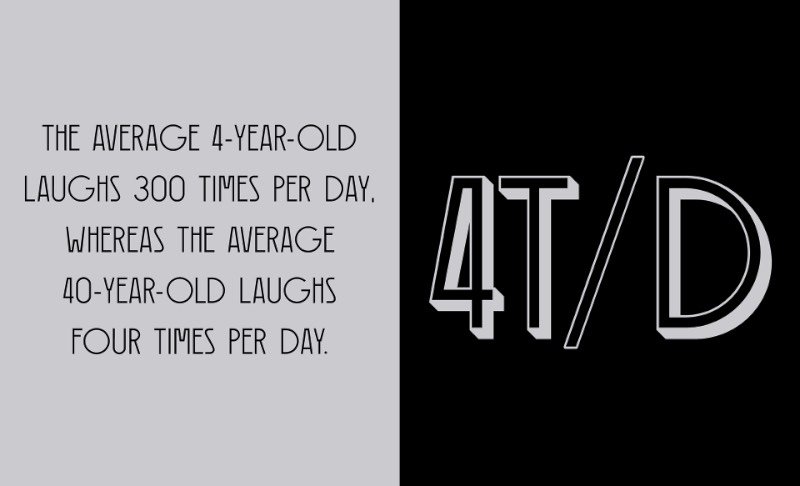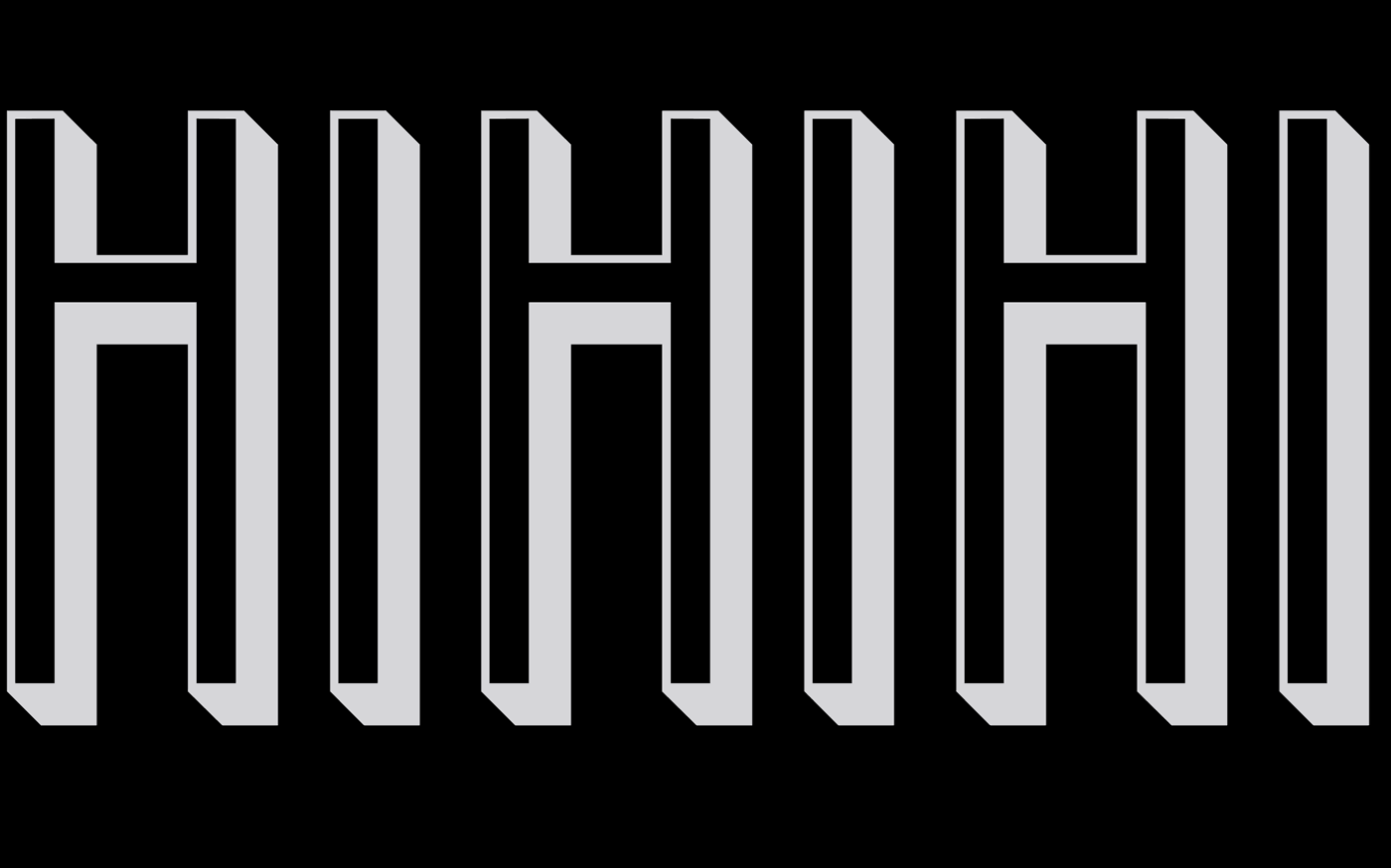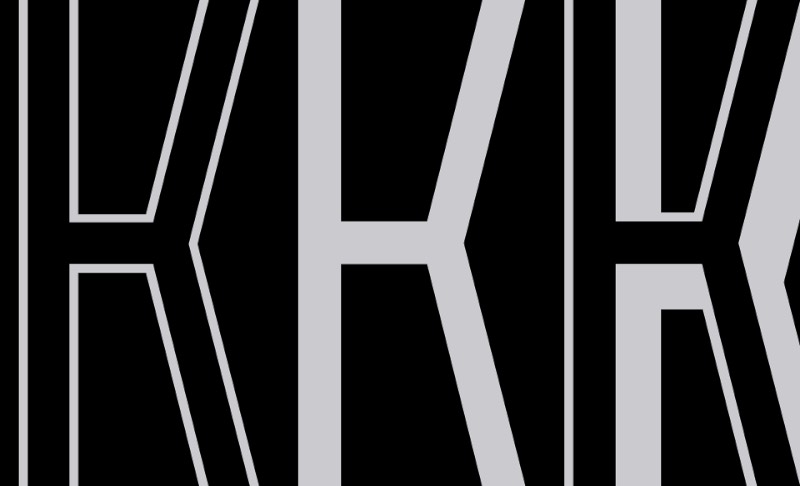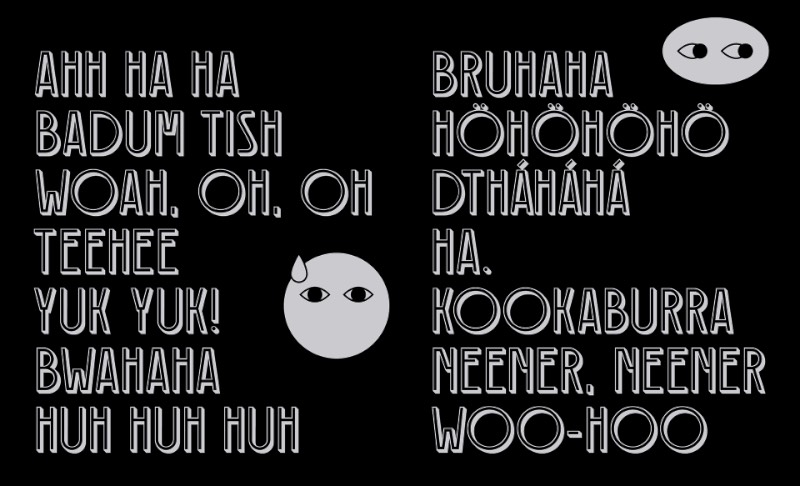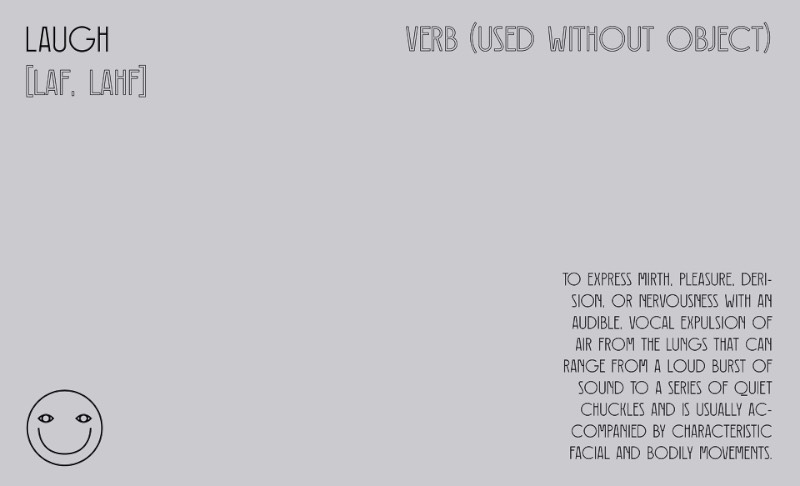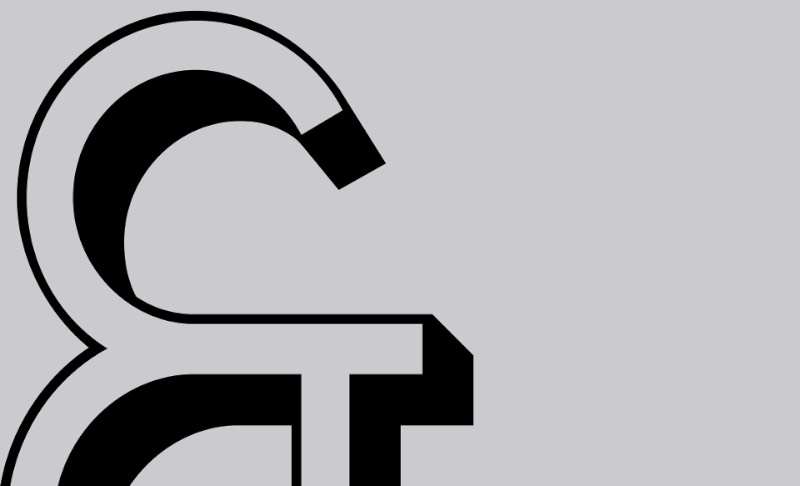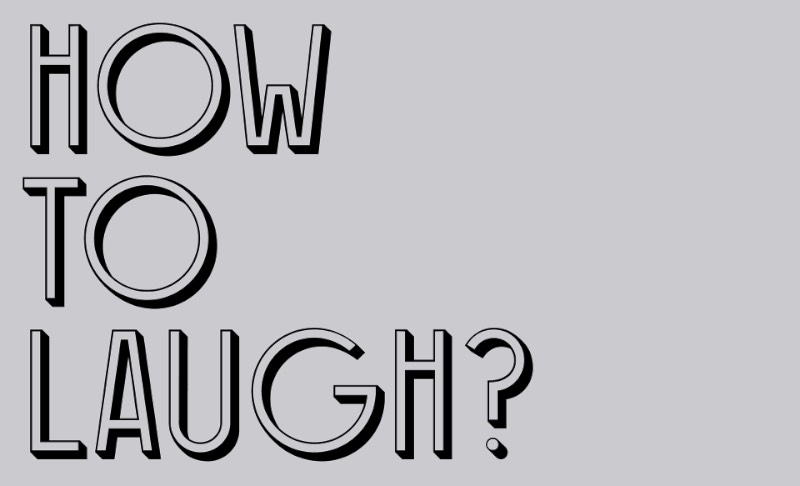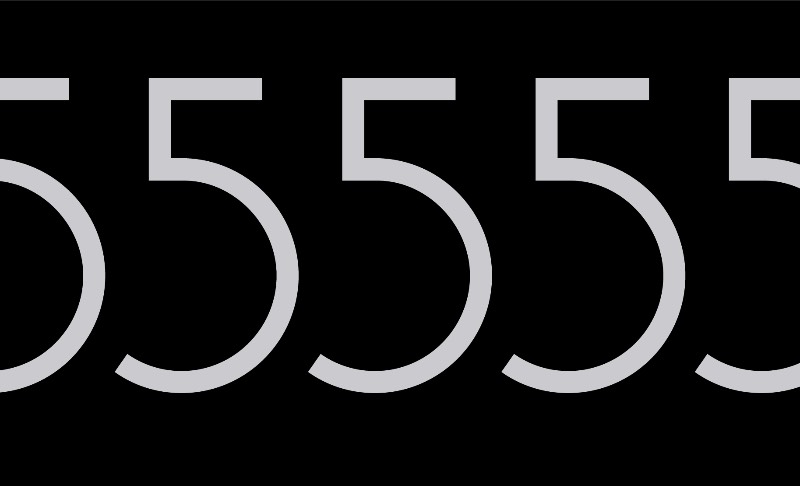
Kookaburra de Kata Moravszki: A Fonte Gratuita da Semana
Kata Moravszki criou a fonte gratuita Kookaburra inspirada por uma série de letras e antigos posters húngaros da década de trinta. O objetivo desse design tipográfico era de criar algo diferente, divertido e que tivesse um visual um pouco estranho. Um visual que pudesse ser complementado por ilustrações e outros elementos gráficos. Esses foram os pensamentos que a designer tinha em mente quando ela criava essa fonte. Afinal, para ela, as risadas e a diversão são os melhores conceitos que ela poderia utilizar em um trabalho como esse.
Foi por esse lado divertido que a fonte acabou recebendo o nome de Kookaburra, o pássaro que faz um som similar a risada humana. E eu acredito que Kata Moravszki conseguiu atingir seu objetivo de criar uma fonte divertida. Afinal, passar os olhos pelas imagens que selecionei dessa fonte me mostram elementos divertidos. Curvas diferentes e letras que tem um equilíbrio visual peculiar. Eu realmente gostei.
Inspired by some secession letters and retro hungarian posters from the ’30s. The aim was when I made the font, make a playful and fresh and a bit strange typeface, which is a good complement to funny illustrations and other graphic elements. When I started to make the font specimen, I thought the laughing and the fun conception are the best topics, how I can present my ideas about use (with illustrations, compositions, spreads).